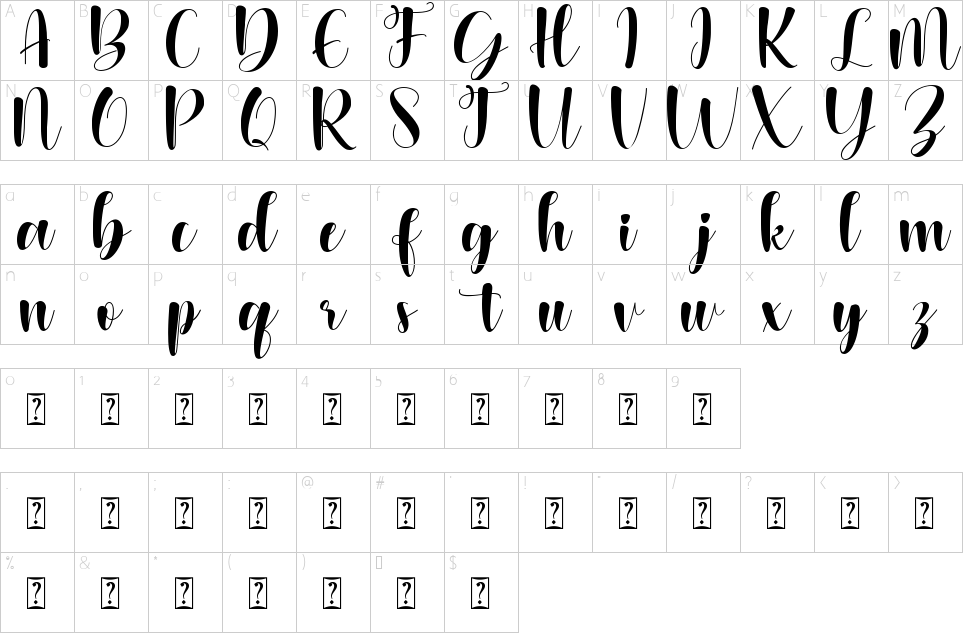
A fonte Pretty Valentine é uma elegante escolha para gráficos e design gráfico, especialmente para datas especiais e aniversários. Desenvolvida pela Nox Studio, essa fonte vem em versões compatíveis com Windows e Mac. Suas características suaves e delicadas tornam-na perfeita para criar elementos de festa, cartões personalizados ou qualquer design que exija um toque romântico e suave. Desde 2019, a fonte Pretty Valentine tem sido adquirida por muitos designers, que apreciam sua capacidade de criar mensagens sutis e agradáveis, tornando-a uma opção atraente para aqueles que buscam uma fonte diferente que adicionará um charme especial ao seu trabalho. Instale e experimente esta fonte, que certamente enriquecerá seu design.